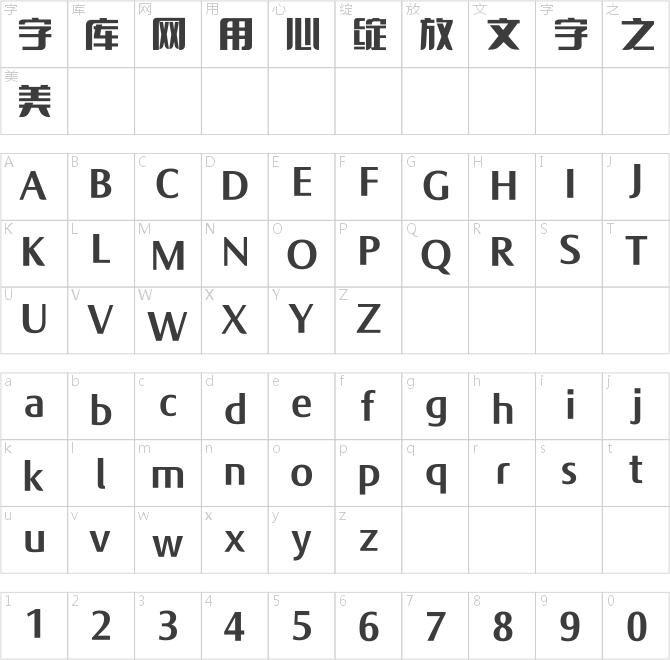
方正字跡-文瀚包裝體 簡 詳情頁
字體名稱: 方正字跡-文瀚
方正字跡-文瀚包裝體 簡
方正字跡-文瀚包裝體 簡字體字庫是一款讓人賞心悅目、百看不厭的中文字體,適合各類廣告和產(chǎn)品包裝設(shè)計應(yīng)用,字體大小1.7MB,格式為ttf字體,上傳用戶是凡塵之間,作者/版權(quán)方為方正字庫